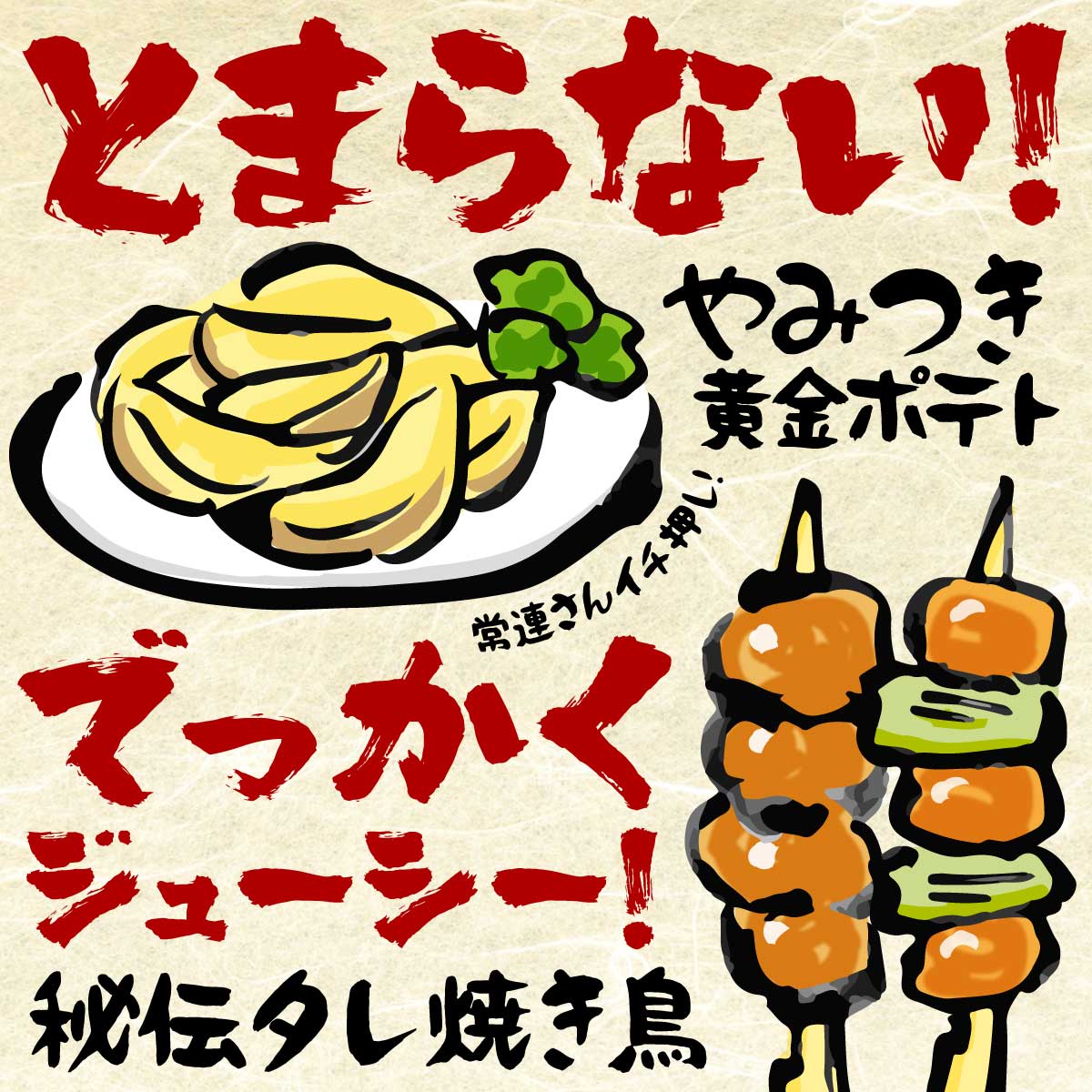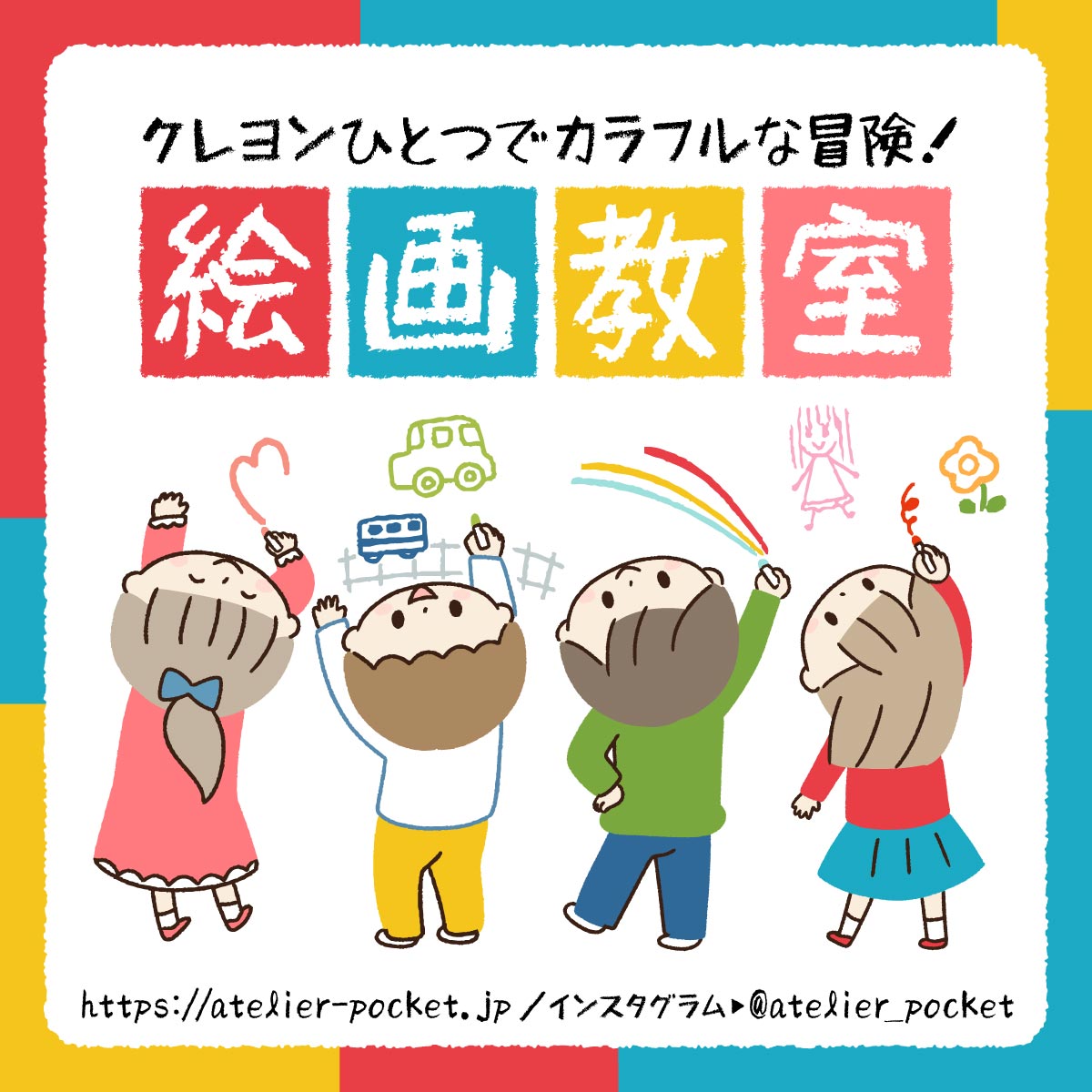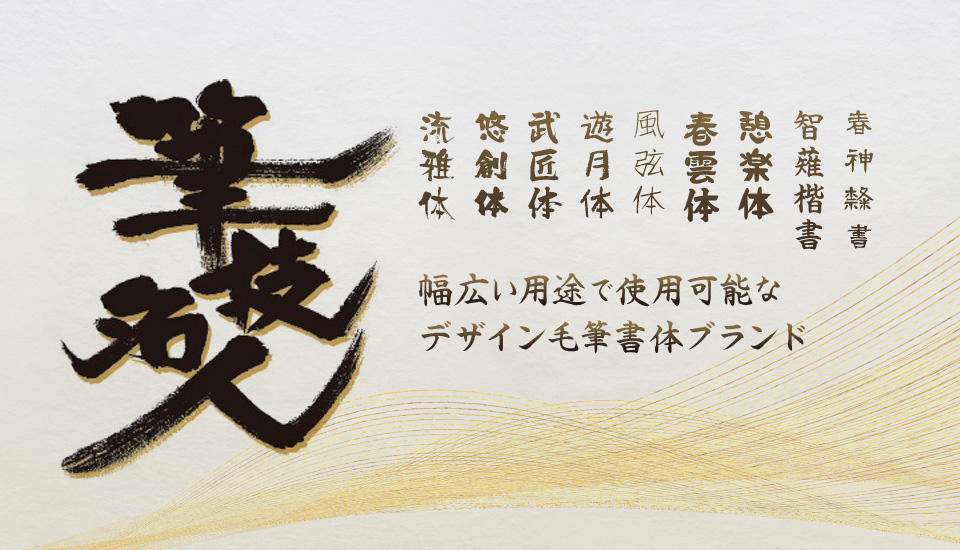
筆技名人フォント 手書きにこだわった毛筆フォントブランド
筆技名人フォント、手書きにこだわった毛筆フォントブランド
経験豊かな書家が心を込めて一文字ずつ書いた手書きの筆文字フォントブランド、ミーネットの「筆技名人フォント」。
筆技名人の特徴
筆技名人フォントは、安価な『毛筆"風"フォント』のように「つくり」や「へん」の流用をせず、一人の書家が書き下ろした3,000〜6,000文字に及ぶ手書きの筆文字を使用しています。
書家と開発者の双方が納得いくまで何度も書き直した筆文字を丁寧にスキャンし、一文字ずつ大きさを調整しながらフォントデータ化。1書体につき、半年から1年以上の時間をかけて開発した、渾身の毛筆フォントです。
手書きの筆文字だからこそ出せる、一文字ごとに違った「かすれ」や「にじみ」。筆技名人フォントは、独自のフォント開発技術で「かすれ」や「にじみ」を出来る限り残し、"生"の文字に近づけるよう工夫しています。
手書きの筆文字ならではの温かみが伝わる、『本物』の毛筆フォントの力を感じてください。
筆技名人 書体ラインナップ
流雅体 (りゅうがたい) 筆技名人 文字サンプル
流雅体 (りゅうがたい)
文字の太さの強弱が絶妙のアクセント。独特のにじみやかすれ具合は書き手特有の個性。「ぬくもりが感じられ印象に残る」「幅広い用途で使える」と好評です。
毛筆書体独特の「かすれ」まで再現した
「極 (きわみ)」タイプもあります
極・流雅体 (きわみ・りゅうがたい) 筆技名人 文字サンプル
極・流雅体 (きわみ・りゅうがたい)
筆技名人フォントの中で最も「かすれ」の多かった流雅体が、最新の技術で生まれ変わりました。データ変換時に失われていた細かい「かすれ」まで再現。毛筆書体独特のかすれの「極み」、他では出せない筆文字フォントの最高傑作です。
悠創体 (ゆうそうたい) 筆技名人 文字サンプル
悠創体 (ゆうそうたい)
力強い太文字でありながら、角張ったフォルムと墨の「かすれ」が生み出すポップな印象。強いインパクトで惹きつける商用の利用実績が最も多い書体です。
毛筆書体独特の「かすれ」まで再現した
「極 (きわみ)」タイプもあります
極・悠創体 (きわみ・ゆうそうたい) 筆技名人 文字サンプル
極・悠創体 (きわみ・ゆうそうたい)
筆技名人フォントシリーズでも一番人気の「筆技名人フォント悠創体」を、最新の技術を使ってデータの取り込みからやり直しました。従来の技術では難しかった筆文字の「かすれ」「にじみ」を完全再現。悠創体の「極み」ここにあり。
武匠体 (ぶしょうたい) 筆技名人 文字サンプル
武匠体 (ぶしょうたい)
行書に近い流れるような筆運びと力強さは、手書きの筆文字ならではの魅力。大きめのロゴはもちろん、小さな文字でも読みやすい万能書体です。
遊月体 (ゆうげつたい) 筆技名人 文字サンプル
遊月体 (ゆうげつたい)
手書きの温もりと子供の頃の懐かしさが甦るクレヨンフォント。クレヨン特有のデコボコ感と際立つ太文字は、インパクトのあるロゴや子供向け商品のタイトルなどに最適です。
風弦体 (ふうげんたい) 筆技名人 文字サンプル
風弦体 (ふうげんたい)
漢字には直線を、平仮名には曲線を多く使うことで、「鋭さ」と「柔らかさ」のメリハリをつけました。極細筆で書いた「弦」のような細字フォントは、長い文章にも向いています。
春雲体 (しゅんうんたい) 筆技名人 文字サンプル
春雲体 (しゅんうんたい)
毛筆独特の「にじみ」が強調された『春雲体』は、楷書をベースに角をなくして丸みをつけることで、力強くありながらも柔らかい印象に仕上げました。
憩楽体 (けいらくたい) 筆技名人 文字サンプル
憩楽体 (けいらくたい)
ポップな筆文字を得意とする書家が『明るく楽しい書体』をコンセプトに書き上げました。食品関係を中心に、幅広いジャンルに使いやすいポップなイメージの丸文字毛筆フォントです。
智薙楷書 (ともなぎかいしょ) 筆技名人 文字サンプル
智薙楷書 (ともなぎかいしょ)
経験豊かな筆耕家が時間をかけて一文字ずつ丁寧に書き上げた、基本の形にこだわった楷書体フォント。手書き文字にしか出せない墨の美しさが映える、正統派で使いやすい書体です。
春神隷書 (はるがみれいしょ) 筆技名人 文字サンプル
春神隷書 (はるがみれいしょ)
隷書体の中でもより古く、篆書に近い字形が特徴的な「古隷」を選んで作りました。とりわけ古隷を得意とするベテランの書家が一文字ずつ魂を込めて書いた、素朴で歴史を感じる隷書体フォントです。